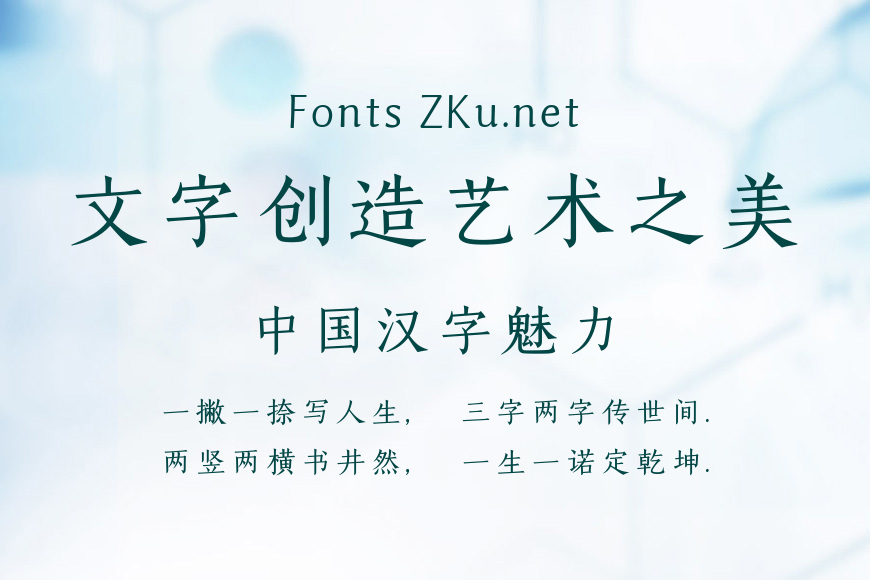
山海汲古宋刻
山海汲古宋刻介绍
山海汲古宋刻是一款国风复古刻本字体,包含简体汉字6763个,字形秉承中国宋代古籍善本之字形特性,版刻刀法剔透,字形方正,起落顿笔有棱角。笔刀结合刚柔并济。在秉承笔形间创新,结合当代设计视觉环境,融入现代审美,适用场景更多元,笔画造型清晰锐利,删繁取简,笔锋凌厉,速度感强,粗细对比强烈,重现刀刻古韵之美。